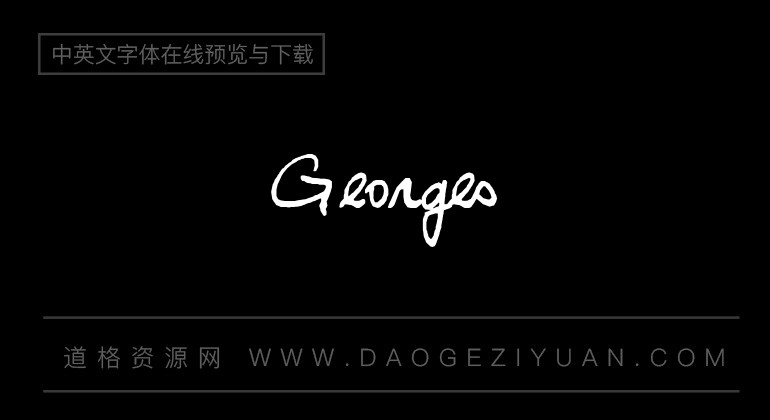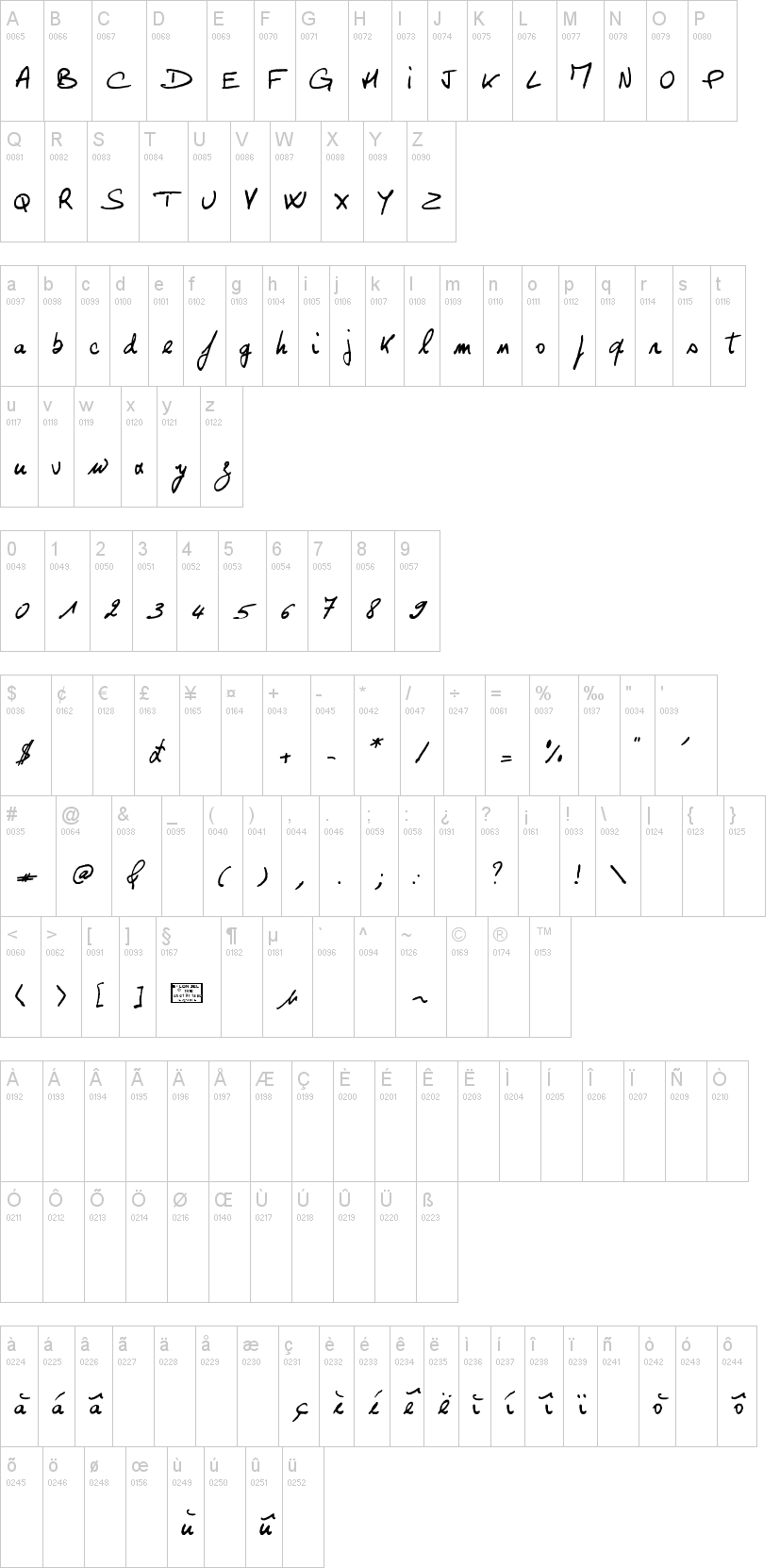
Georges
Georges 字体是一款由美国设计师 Georges Peignot 创作的现代派字体。它拥有细腻的线条和柔和的曲线,整体形状优美,极具特色,充满现代感。字体的字形设计比较规整,每个字母都有细微的变化,而且十分精细,极具视觉冲击力。Georges 字体非常适合用于标题、标识、标牌、海报等场景,可以给视觉效果增添一份活力。
Georges是一款非常不错的手写艺术字体,具有很好的视觉感,适合于文化类的宣传设计、商业类品牌的广告和产品包装设计以及个性化文字排版等较多场景。